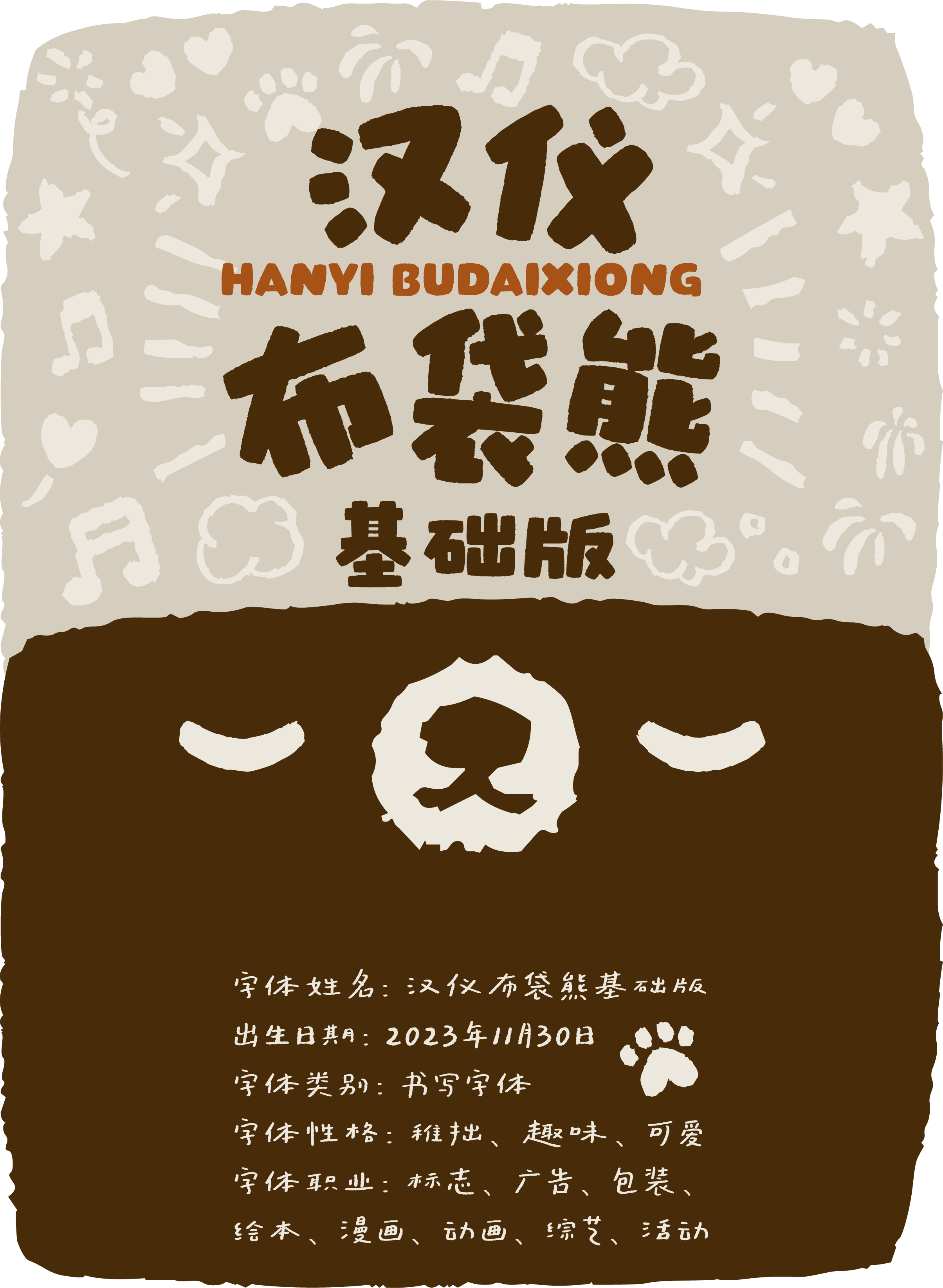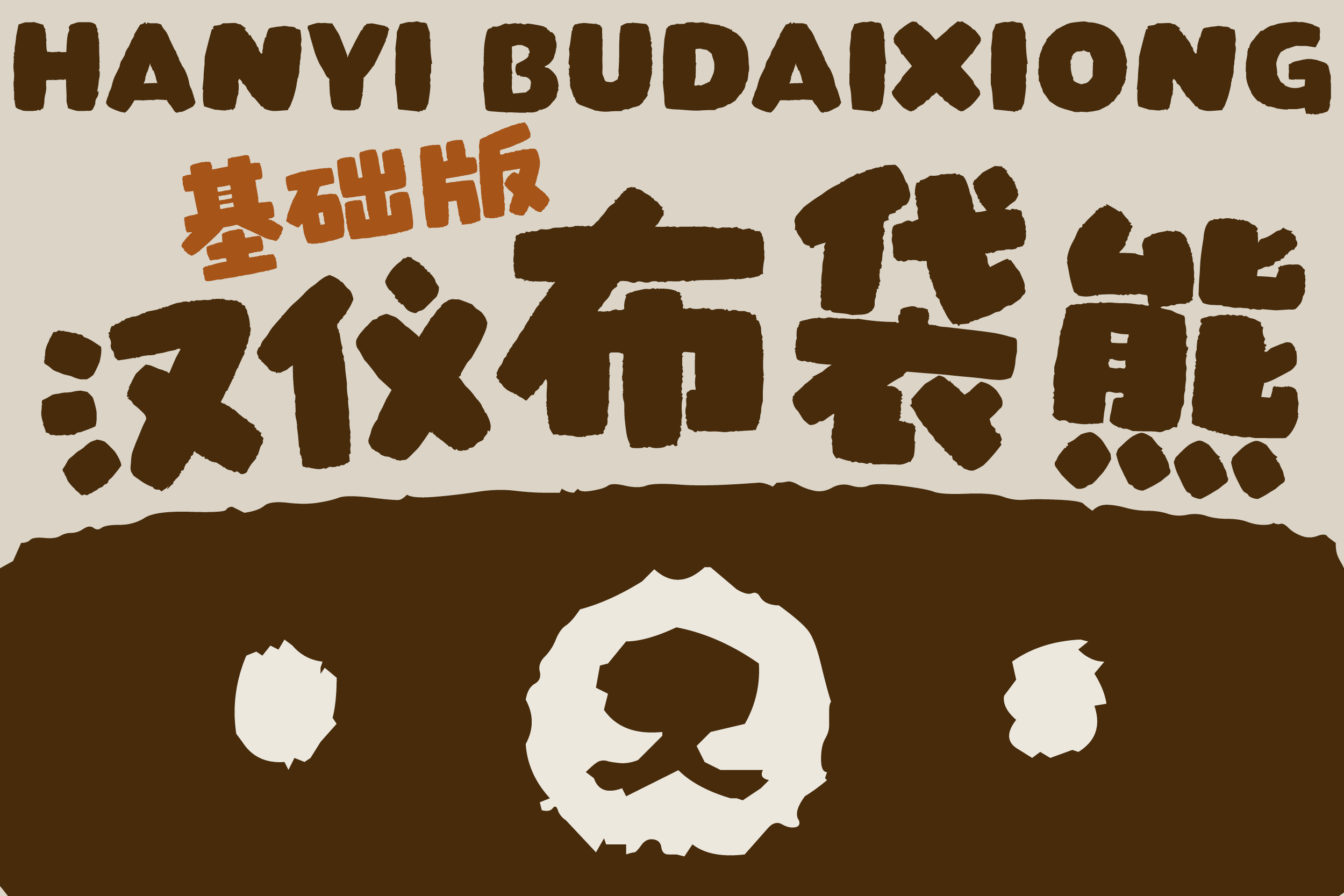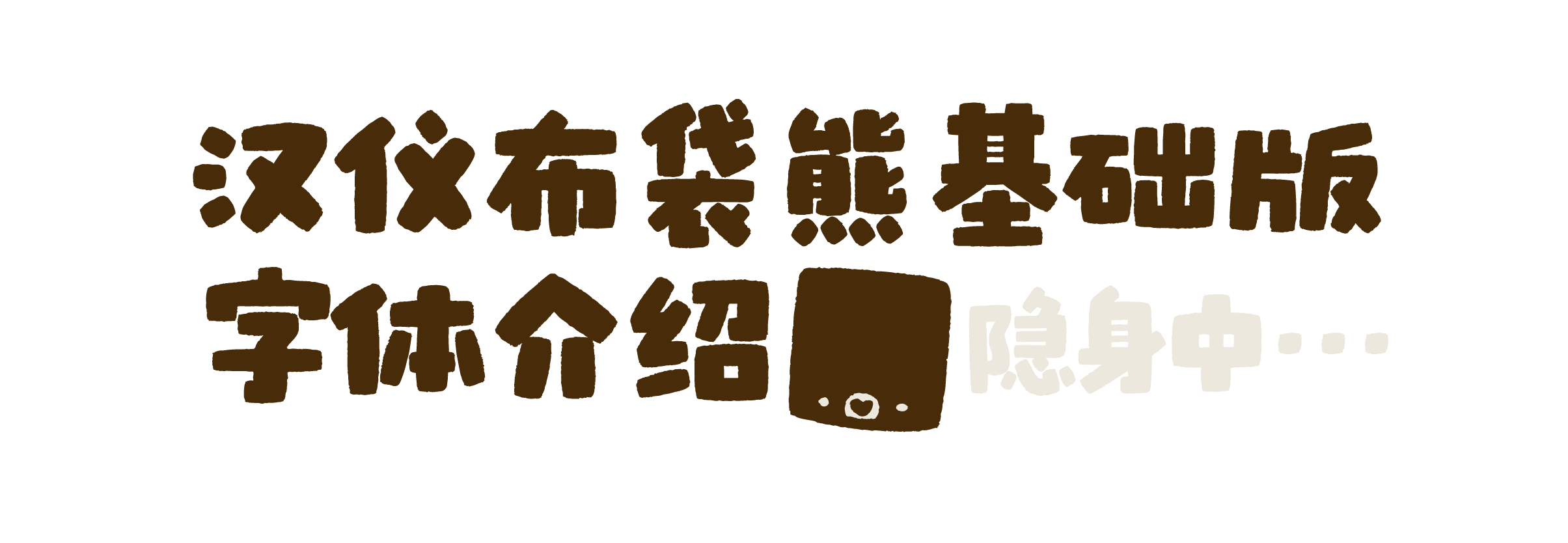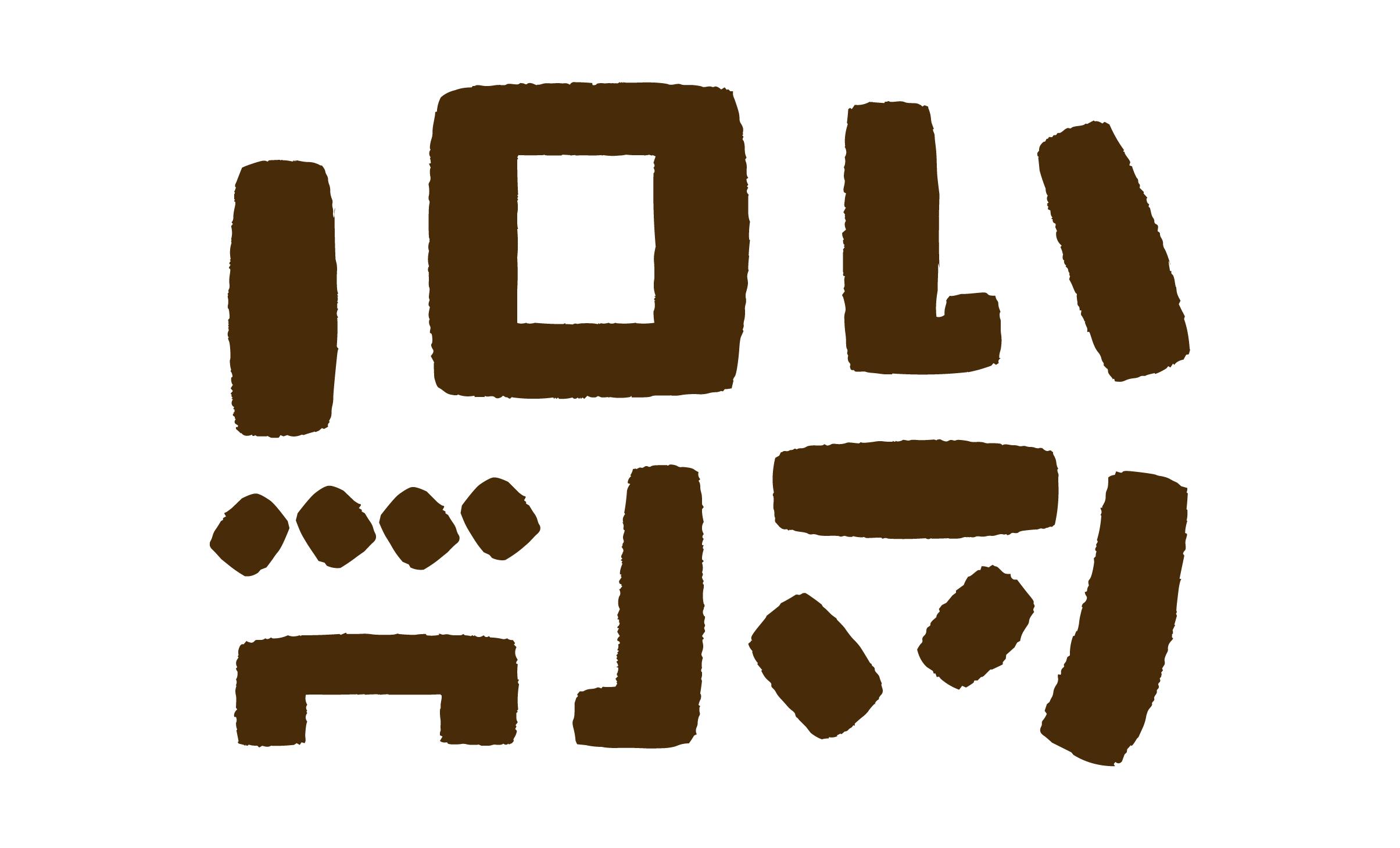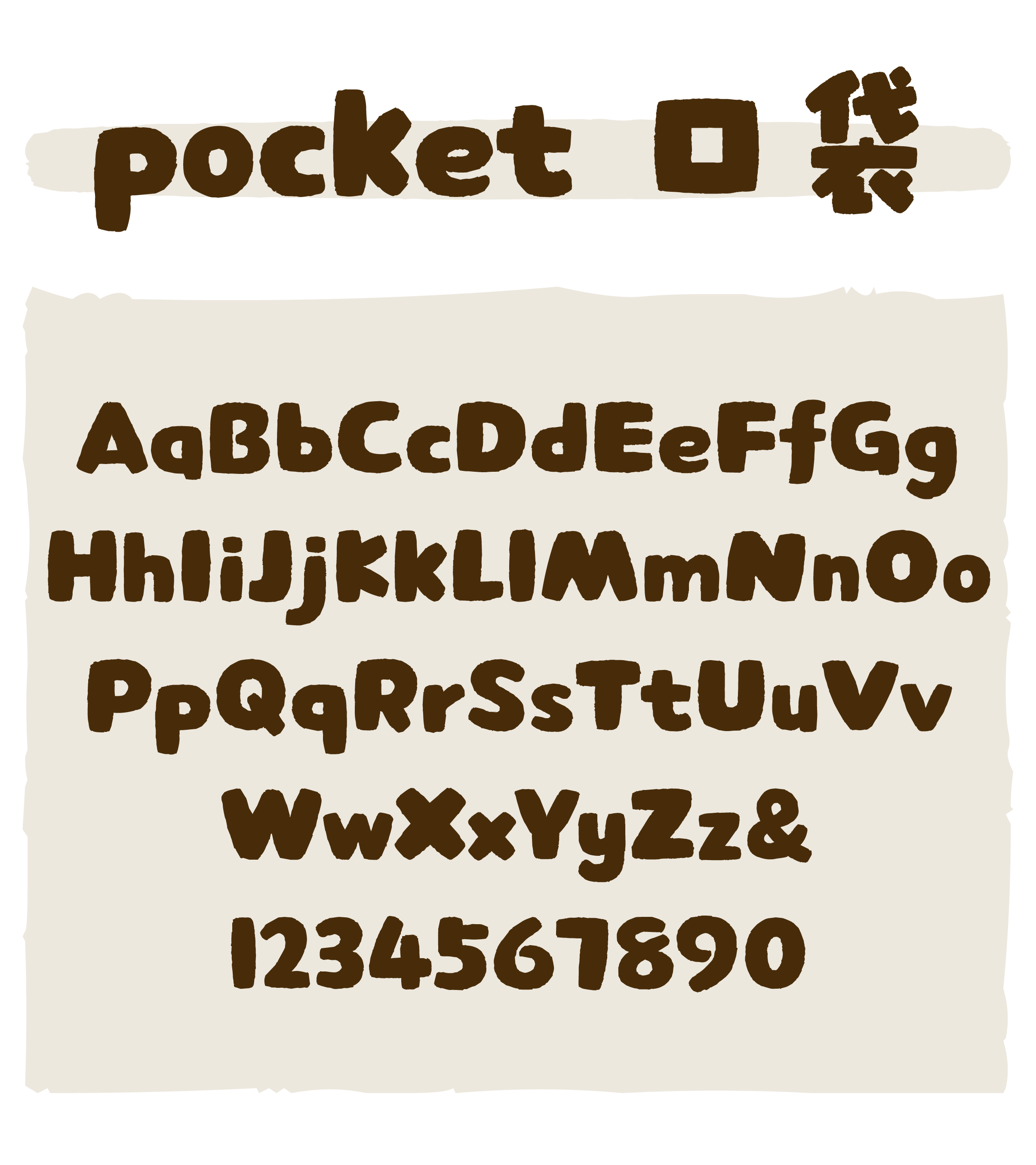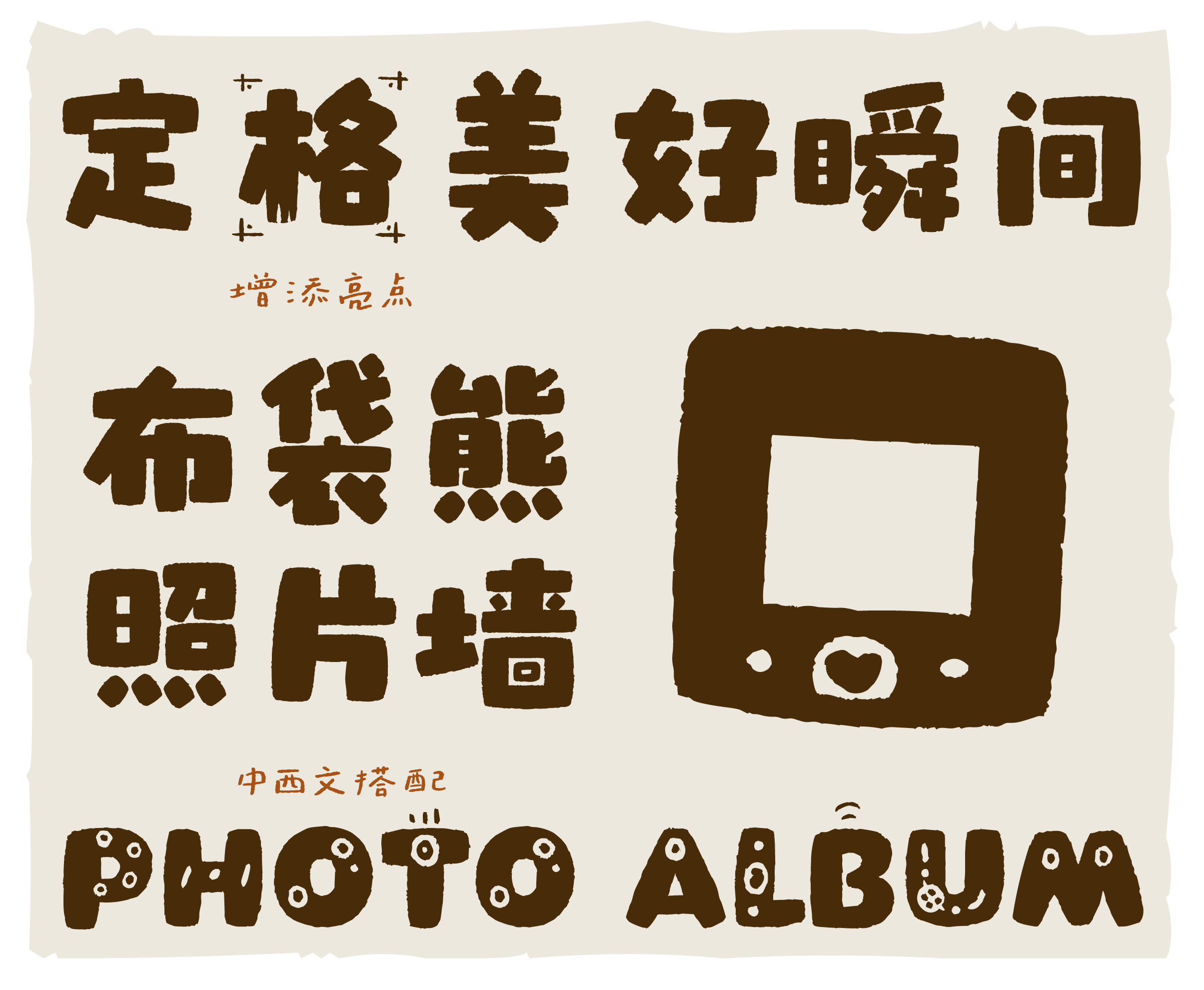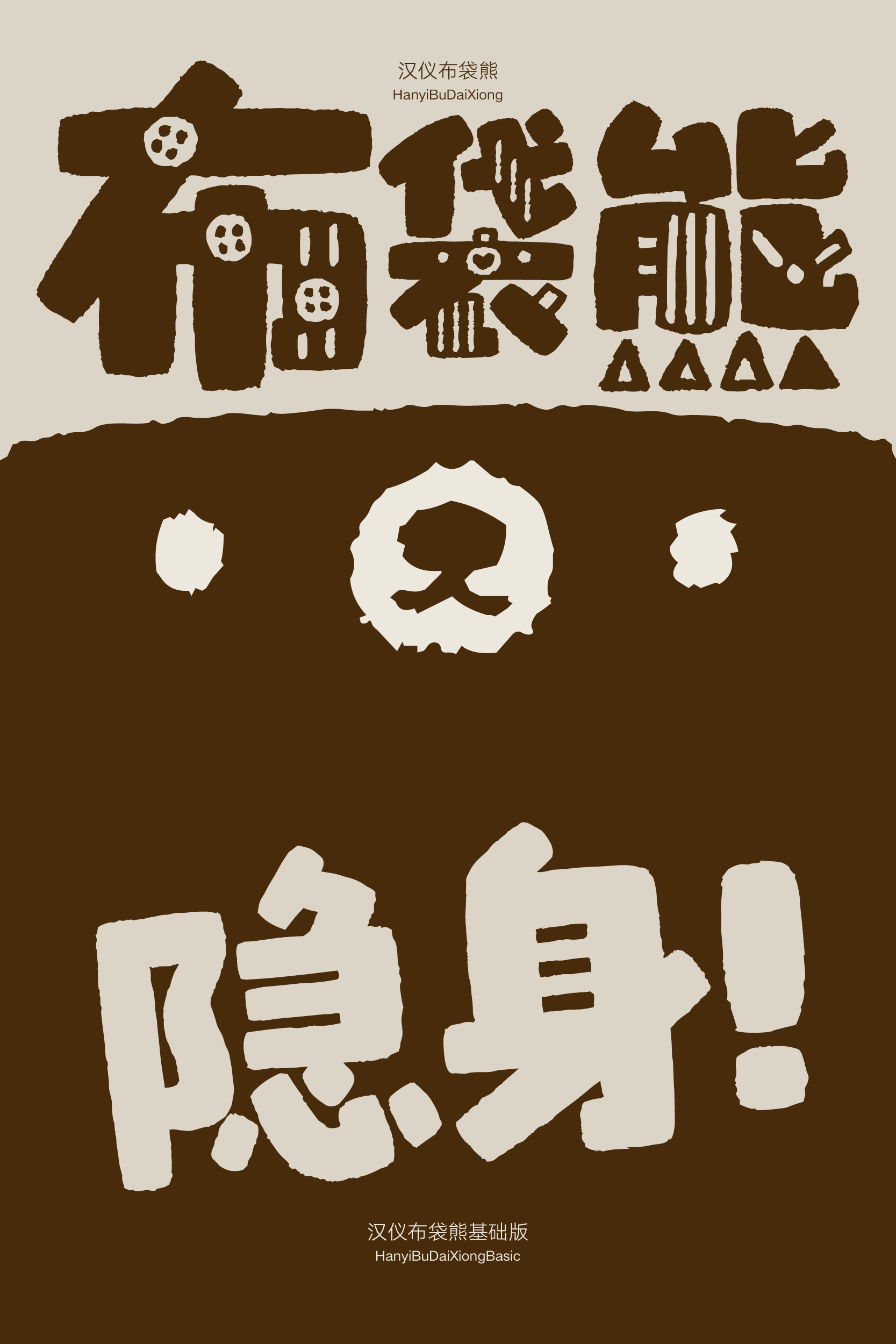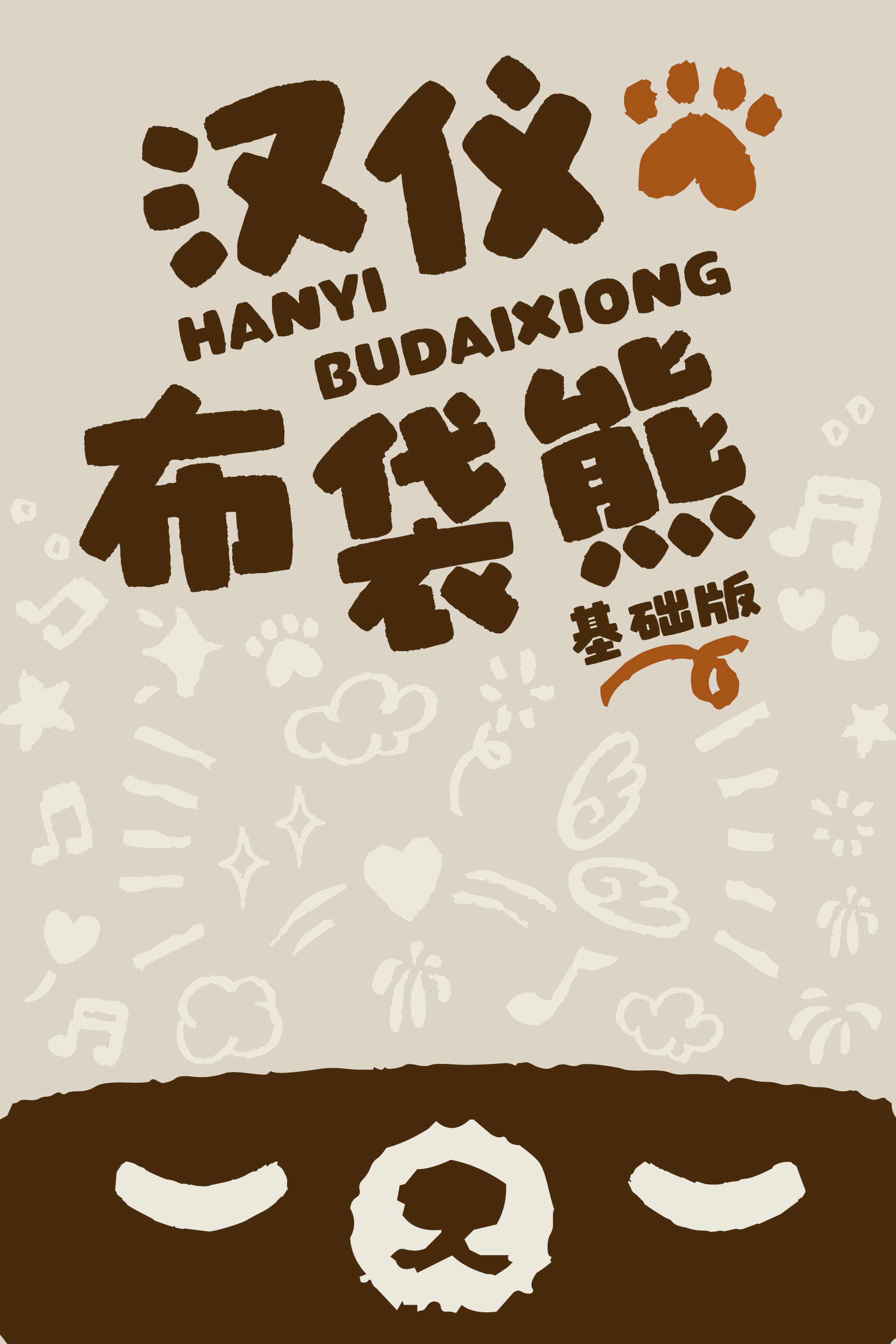
送你一只圆鼓鼓的布袋熊
汉仪布袋熊基础版是汉仪布袋熊“隐身”之后的基础字形,大大小小的方块字形整齐中有着活泼的变化,笔画如同圆鼓鼓的布袋,有膨胀感。这款手写字体适用标题或较短文本的排版,推荐与汉仪布袋熊搭配,应用于漫画绘本、综艺影视、广告包装等不同场景。
汉仪布袋熊基础版,方形的基础字形,字面大小错落,整齐中有着活泼的变化。
笔画如同圆鼓鼓的布袋,有膨胀感。
西文部分的字形同样饱满活泼,中西文风格一致。
“隐身”的汉仪布袋熊基础版,省略了装饰元素,仍然可以作为一款童趣满满的标题字体,推荐与汉仪布袋熊搭配使用,增添亮点,满足更为广泛的使用场景。